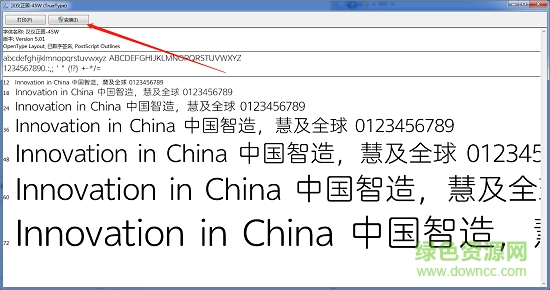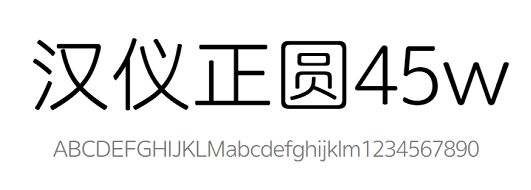
漢儀正圓45w字體是一款看起來(lái)非常舒適的字體,正圓字體,整體看起來(lái)比較圓潤(rùn)舒適,非常適合日常文章的排版寫(xiě)作中,簡(jiǎn)單干練,喜歡就來(lái)綠色資源網(wǎng)下載吧!
漢儀正圓字體是一款美觀大方的中文字體,這款字體排版非常的整齊,字跡清晰,具有很好的視覺(jué)效果,適合應(yīng)用與藝術(shù)設(shè)計(jì)、平面宣傳設(shè)計(jì)、書(shū)籍雜志設(shè)計(jì)等領(lǐng)域,需要的朋友可以前來(lái)本站下載!